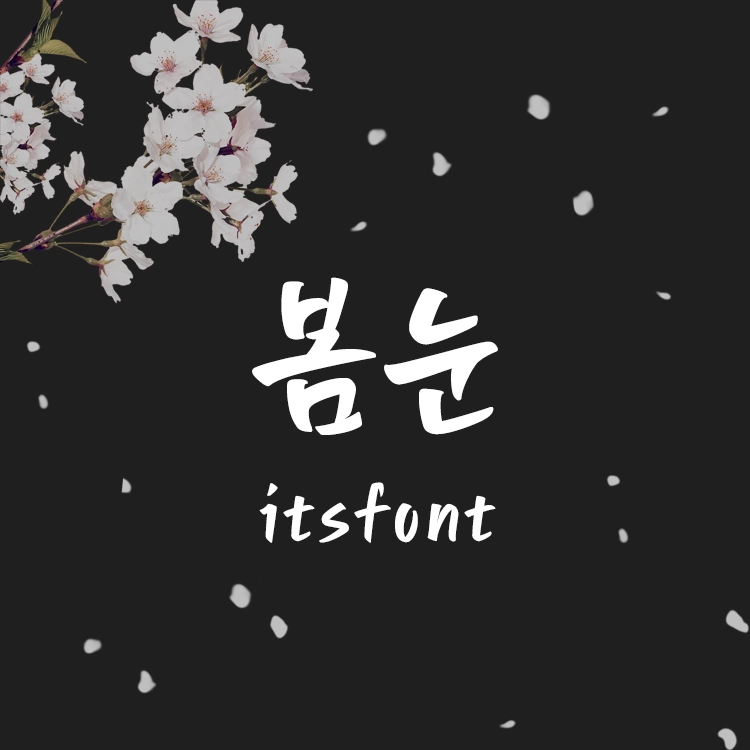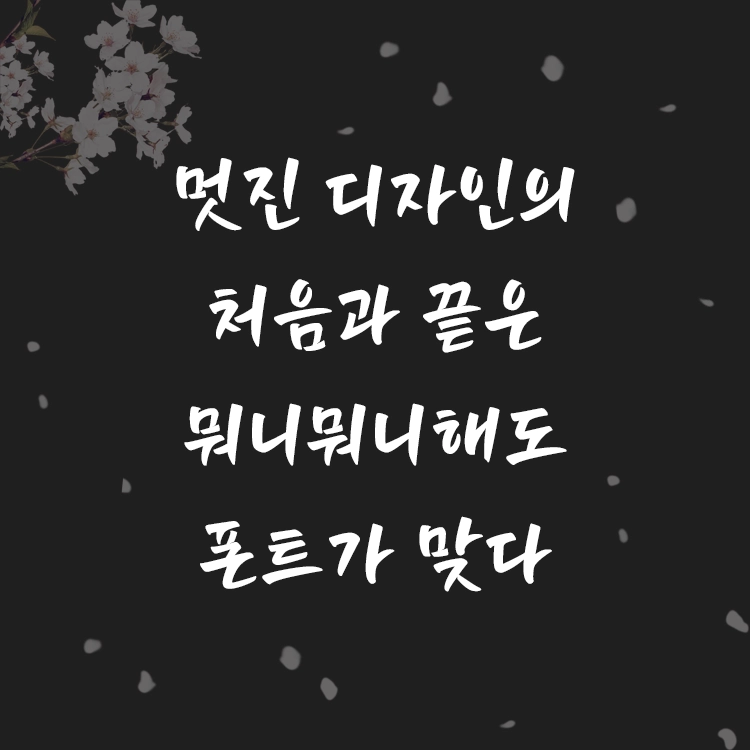
'봄눈'은 붓으로 쓴 손글씨를 기반으로 만들어진 제목용 캘리그라피 폰트입니다.
작은 크기로 쓰이는 본문용 쓰임보다는 큰 쓰임의 환경에서 본래의 손맛이 잘 표현될 수 있도록 디자인되었습니다. 특히 크게 쓰였을 때 붓으로 표현된 허획 요소, 붓질감 등의 서체 특징이 더욱 효과적으로 드러날 수 있습니다.